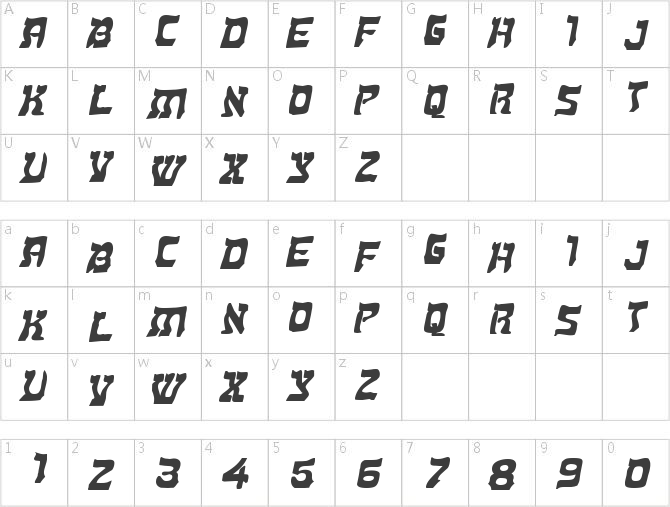
Kosher-Extended-BoldItalic
Kosher-Extended-BoldItalic介绍
Kosher-Extended-BoldItalic字体字库是一款让人赏心悦目、百看不厌的英文字体,适合各类广告和产品包装设计应用,字体大小0.08MB,格式为ttf字体,上传用户是Elieen,作者/版权方为未知